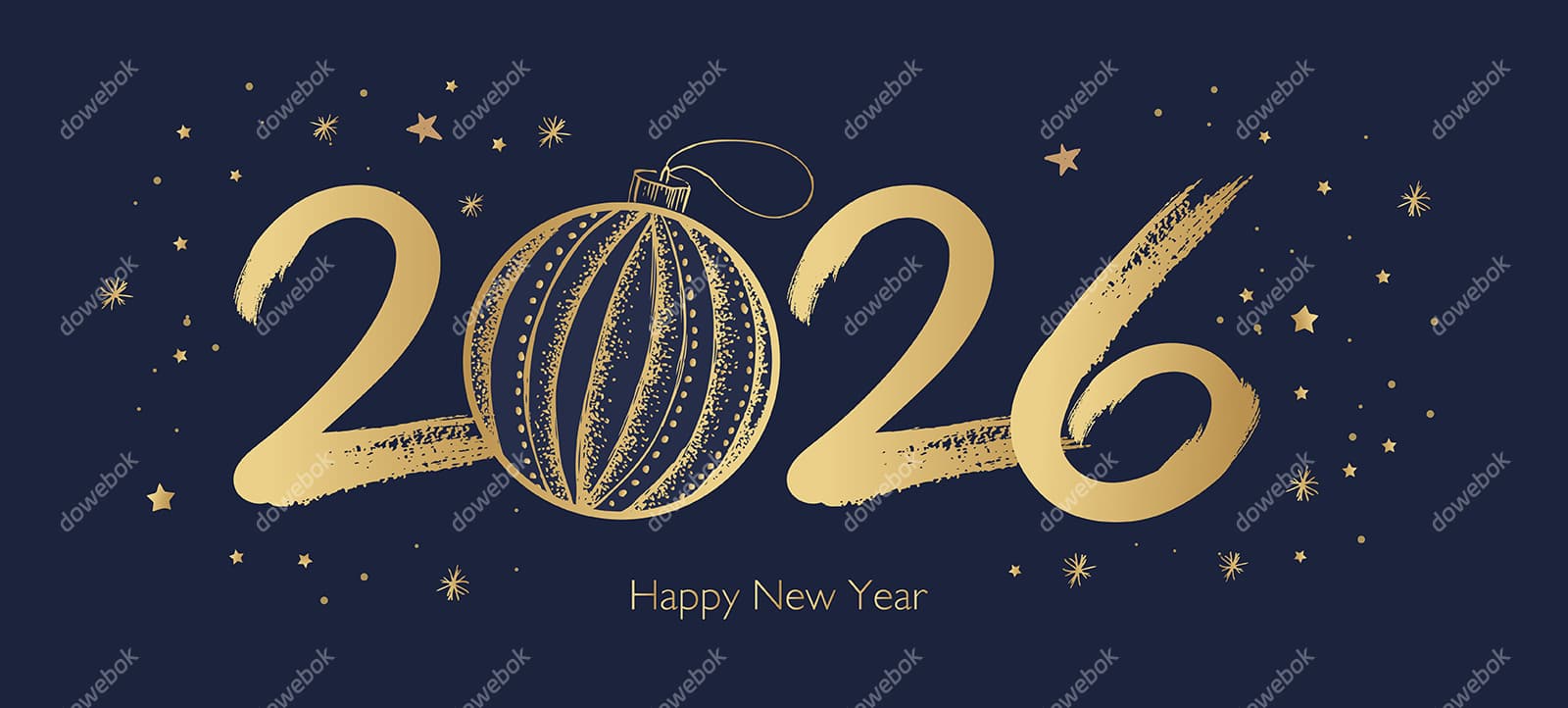
这是一款圣诞装饰球和金色数字设计 2026 新年快乐矢量素材,深蓝背景上,金色 “2026” 以笔触质感呈现,数字 “0” 替换为带纹理的装饰球,似节日挂饰灵动俏皮。周围散落的星点光斑添了梦幻感,下方衬着简约的 “Happy New Year”。整体以墨蓝底色配鎏金元素,笔触肌理与装饰细节交织,既显跨年的雅致氛围,又透出节日的温馨与精致。